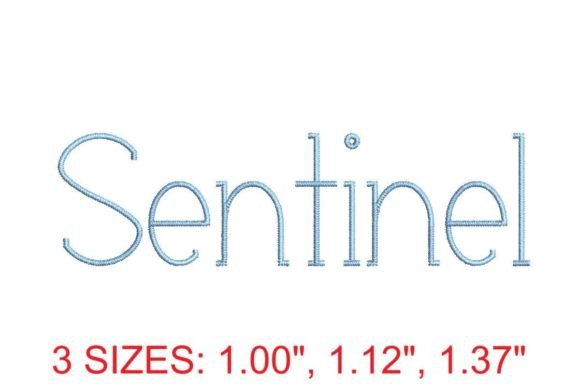
Sentinel Font
Ulasan Terperinci: Sentinel Font – Font Sulaman Elegan & Serba-Guna untuk Mesin Jahit Elektronik
Sentinel Font bukan sekadar font sulaman biasa — ia adalah pilihan utama para penggiat kraf digital di UK yang mengutamakan ketepatan, keanggunan, dan kompatibilitas tanpa cela. Dibangunkan khusus untuk dunia sulaman mesin, font ini menawarkan sentuhan klasik-modern yang sempurna untuk monogram eksklusif, nama personal pada kain berkualiti tinggi, atau teks dekoratif pada projek fesyen dan hadiah tangan.
- Rekaan Mewah: Garisan bersih, proporsi harmoni, dan jarak antar-huruf yang dioptimumkan — hasil akhirnya kelihatan profesional, sama ada pada kapas, linen, atau bahan berstruktur tinggi.
- Kebolehgunaan Tinggi: Ideal untuk monogram keluarga, label pakaian, kain bayi, hadiah perkahwinan, dan projek komersial kecil — semua dengan satu set yang serba boleh.
Jika anda mencari font sulaman yang menggabungkan keanggunan zaman Victoria dengan ketepatan teknikal moden — dan yang benar-benar ‘siap pakai’ untuk mesin jahit anda hari ini — Sentinel Font adalah jawapan yang tidak perlu dipertikaikan. Ia bukan sekadar menambah teks ke kain; ia meningkatkan nilai, daya tarikan, dan kehalusan setiap projek anda — satu jahitan pada satu masa.